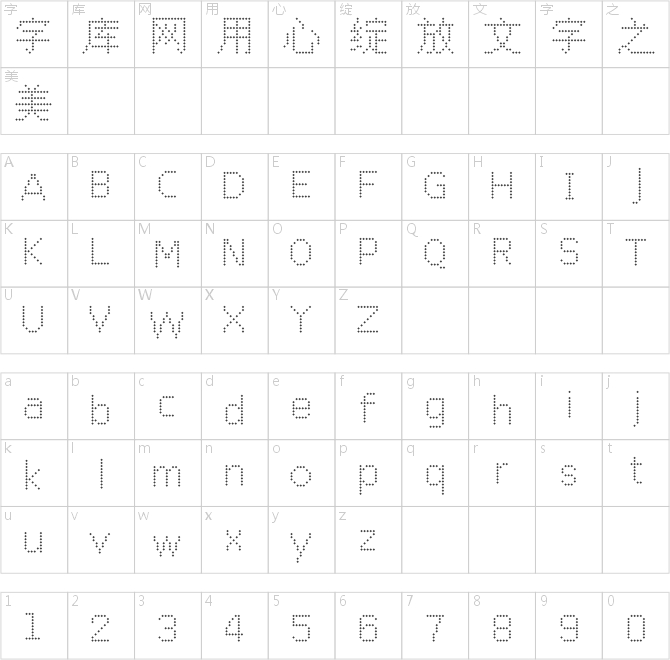
字体名称: 点点像素
点点像素
点点像素字体下载DottedSongti
点点中文像素字体是一组基于GPL 2.0协议开源发布的中文像素艺术字体,每种字体均支持超过22000个Unicode字形,覆盖GBK编码中的全部简繁体汉字。
目前发布的点点像素字体都是基于文泉驿项目所创建的一 种点阵字体衍生而来的。它们是文泉驿点阵宋体经矢量化之后,通过变形、美化而得到的。文泉驿点阵宋体是基于GPL 2.0协议开源的自由字体。请访问wenq.org以获取该字体的更多信息。
参考 converter/中的源代码。该代码自动将文泉驿点阵宋体中的字型矢量化,然后变形加工为不 同风格的 OpenType 字体。在下载的字体文件包中,包括三个字体文件,主要的区别是字体的点的形状不一样。有三个样式,一个是圆形的点,一个是方形的点,还有一个是菱形的点。
目前发布的点点像素字体都是基于文泉驿项目所创建的一 种点阵字体衍生而来的。它们是文泉驿点阵宋体经矢量化之后,通过变形、美化而得到的。文泉驿点阵宋体是基于GPL 2.0协议开源的自由字体。